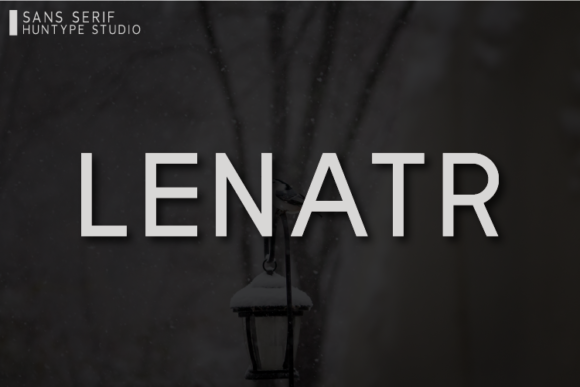
Lenatr
การค้นหาองค์ประกอบการออกแบบที่เหมาะสมอาจเป็นเรื่องท้าทาย แต่ Lenatr นำเสนอคอลเลกชันที่โดดเด่นซึ่งช่วยยกระดับงานของคุณได้ทันที
ไม่ว่าคุณจะสร้างผลิตภัณฑ์ POD (Print on Demand) คำเชิญงานแต่งงาน หรือกราฟิกโซเชียลมีเดีย Lenatr ก็เหมาะสมอย่างยิ่ง